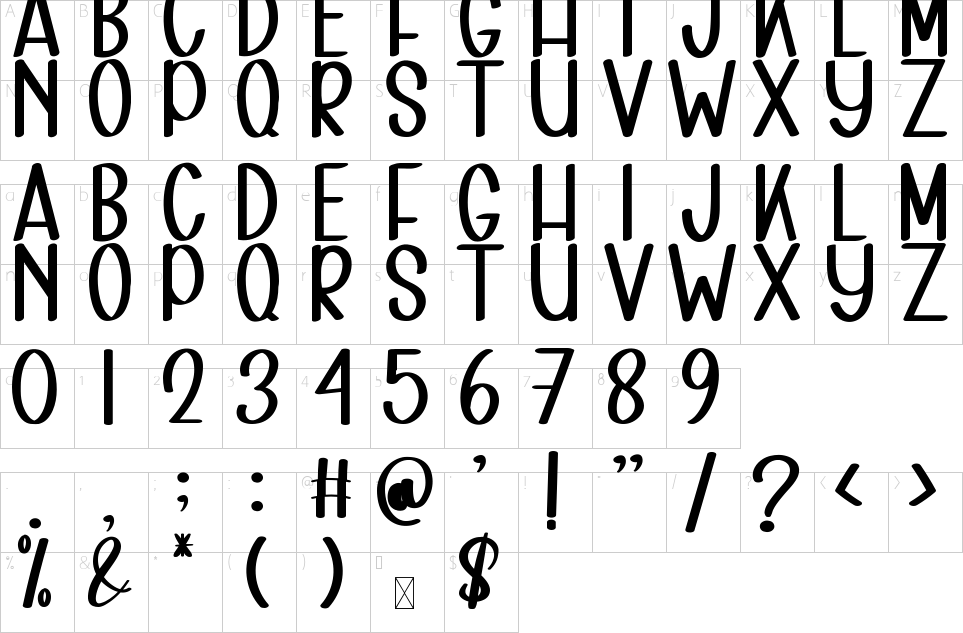
Aqui está uma descrição em português para a página de download da fonte ‘Minimalis Highland’ para a categoria de fontes gratuitas: Através de seu design simples e elegante, a fonte Minimalis Highland oferece uma sensação de minimalismo e sofisticação ao seu projeto. Desenvolvida pelo InermediaSTUDIO, esta fonte está disponível para sistemas Windows e Mac, permitindo que você personalize seu design de maneira clara e contemporânea. Com seu design limpo e minimalista, esta fonte é perfeita para projetos de design gráfico que buscam um equilíbrio entre clareza e simplicidade. Recomendada para criações de design digital como logos, materiais de marketing e até mesmo para o layout de sites, a Minimalis Highland é uma ótima escolha para quem busca uma fonte que se adapta ao seu design de maneira precisa e elegante. Seja você um designer profissional ou iniciante, esta fonte é uma ótima adição à sua coleção de recursos gráficos.